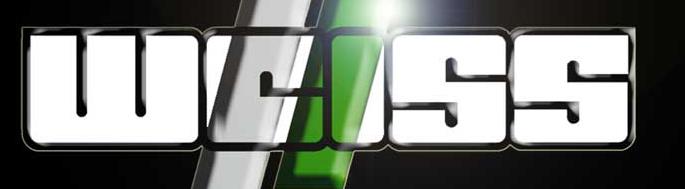
Schriftart aus Grafik gesucht
ich suche verzweifelt nach der Schriftart die für das Wort "WEISS" in der angehängten Grafik verwendet wurde.
Das "Logo" wurde vor mehr als 15 Jahren erstellt. Leider ist der Ersteller mittlerweile verstorben, so dass ich den nicht mehr fragen kann. Die Schrift besteht eigentlich nur aus den weißen Buchstaben, ohne den dicken schwarzen Rand.
Kennt einer von Euch so eine Schriftart?
Sehr gut möglich, dass der Ersteller  das Logo gänzlich ohne eine Schtiftart zu nutrzen gezeichnet hat. Ich jhabe ja schon einige meiner Schriftarten nach solchen Logos gemacht, aber da passiert es nicht selten, dass ich allein bei der Analyse der vorhandenen Buchstaben erkenne, dass daraus gar kein komplettes Alfabet zzu machen ist, weil einige Buchstaben sich einfach nicht in die Formen der Logo-Buchstaben quetschen lassen.
Würde ich ein Logo erstellen, würde ich mich zwar auch entfernt von einer Schriftart inspirieren lassen, dann aber die oft wenigen Buchstaben mehr frei konstruieren, um so zu einem gut einzigartigen Logo zu kommen, dass sich dann auch gut schützen lässt, und sich eben nicht so einfach nachsetzen lässt.
Auch ähnlich, und nach einem ähnlich konstruierten Logo entstanden (auch eine Anfrage hier)
oder etwas anderes, das hier noch so eine Logo-Frage war:
Ich schätze mal, dass sich das Logo in weniger als einer halben Stunde so zeichnen lässt, die Suche nach der passenden Schrift dauert unter Garantie länger, daher würde ich mich immer zuerst fragen: Wie schnell läst sich das wirklich genau zeichbnen, bevor ich mich auf die Schriftsuche begebe.